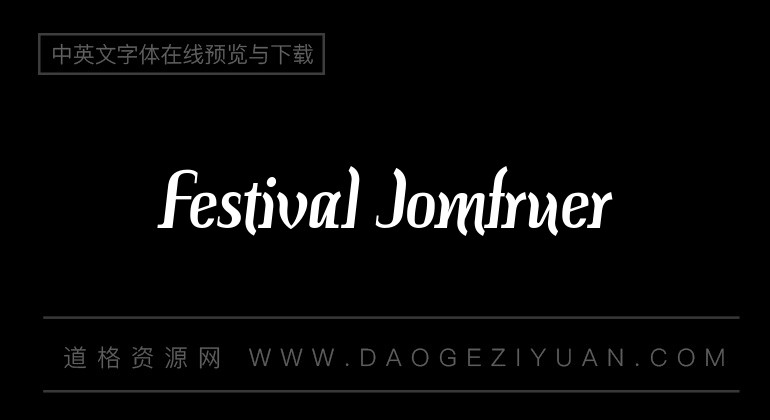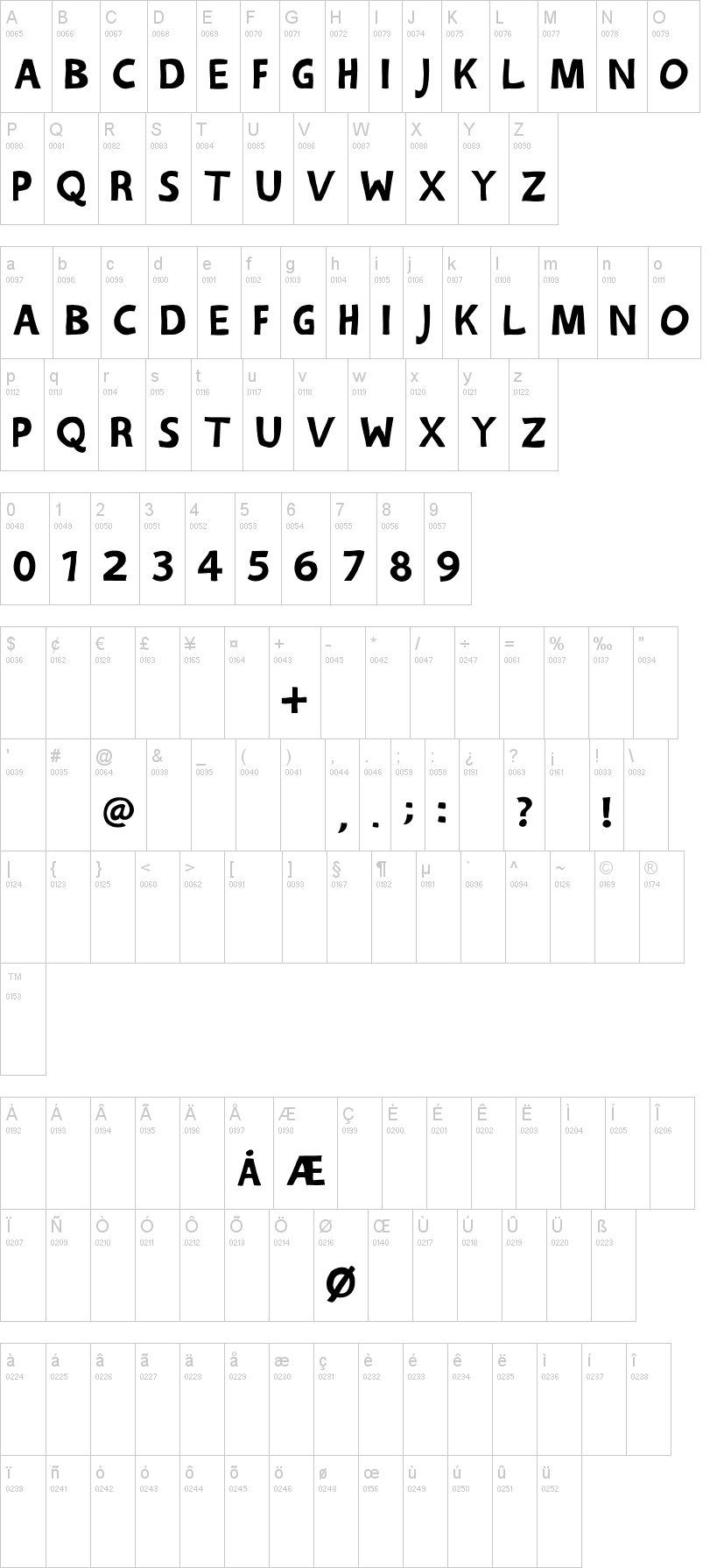
Festival Jomfruer 是一种手写风格的字体,具有轻松、自然和优美的特点。它的设计灵感来自斯堪的纳维亚半岛的节日和传统。 该字体包括大写字母、小写字母、数字和标点符号。它的线条流畅,非常适合用于海报、广告、标志、包装、菜单、贺卡、书籍等设计中。 Festival Jomfruer 字体有多种不同的字重可供选择,包括 Regular、Bold、Light 和 Extra Light 等,这些字重的组合可以满足不同设计需求。 此外,该字体还支持多种语言,包括英语、德语、法语、意大利语、西班牙语和葡萄牙语等。内容介绍
Festival Jomfruer是一款非常不错的手写艺术字体,具有很好的视觉感,适合于文化类的宣传设计、商业类品牌的广告和产品包装设计以及个性化文字排版等较多场景。